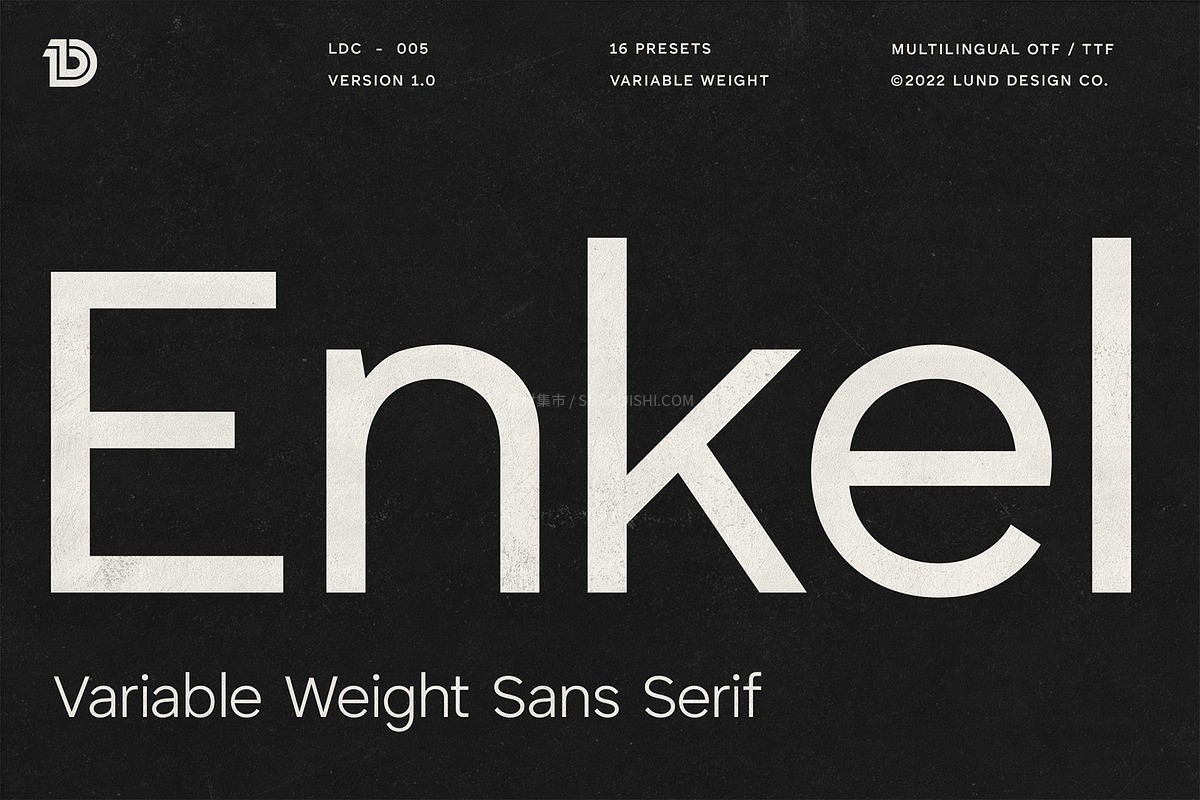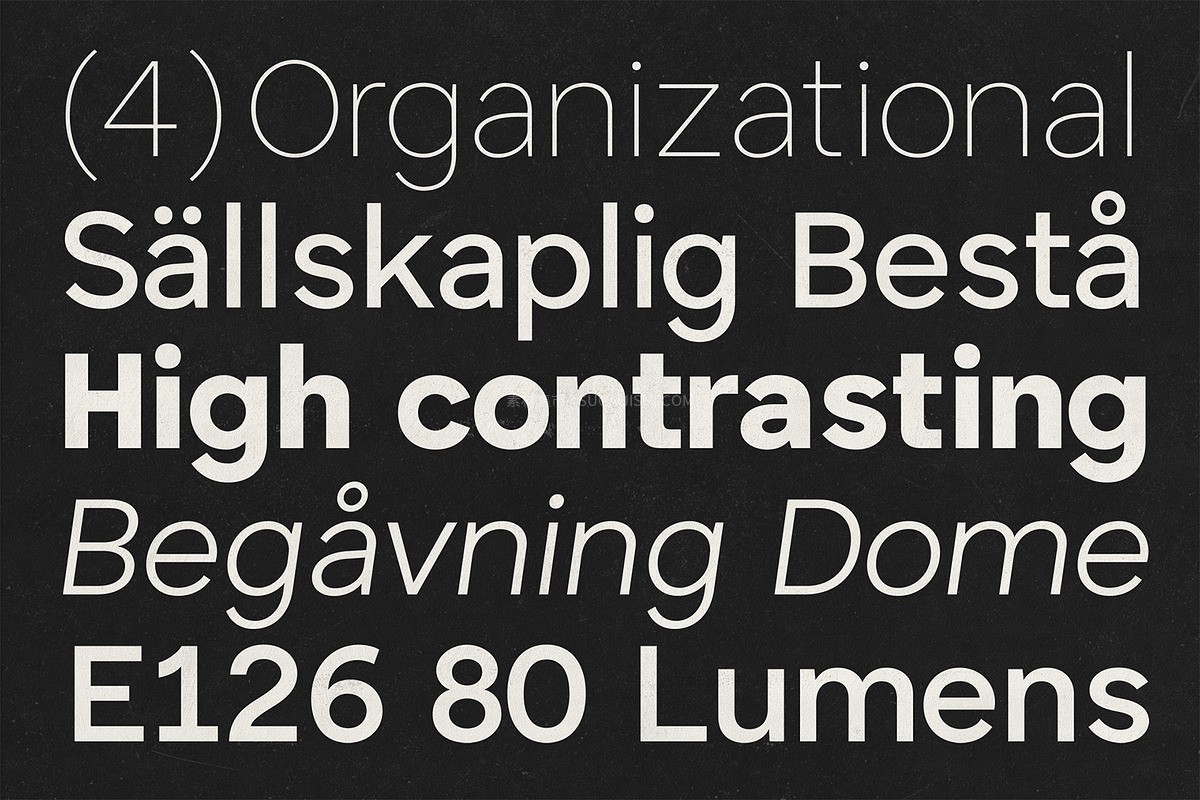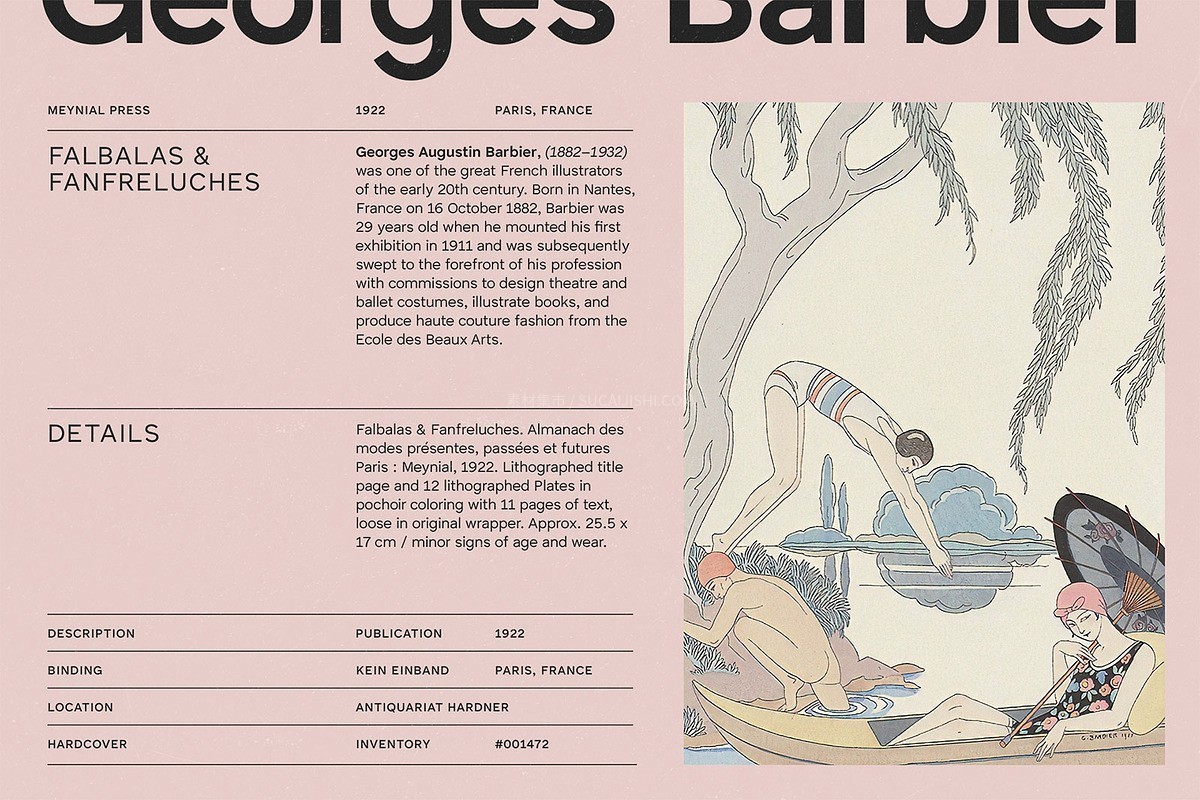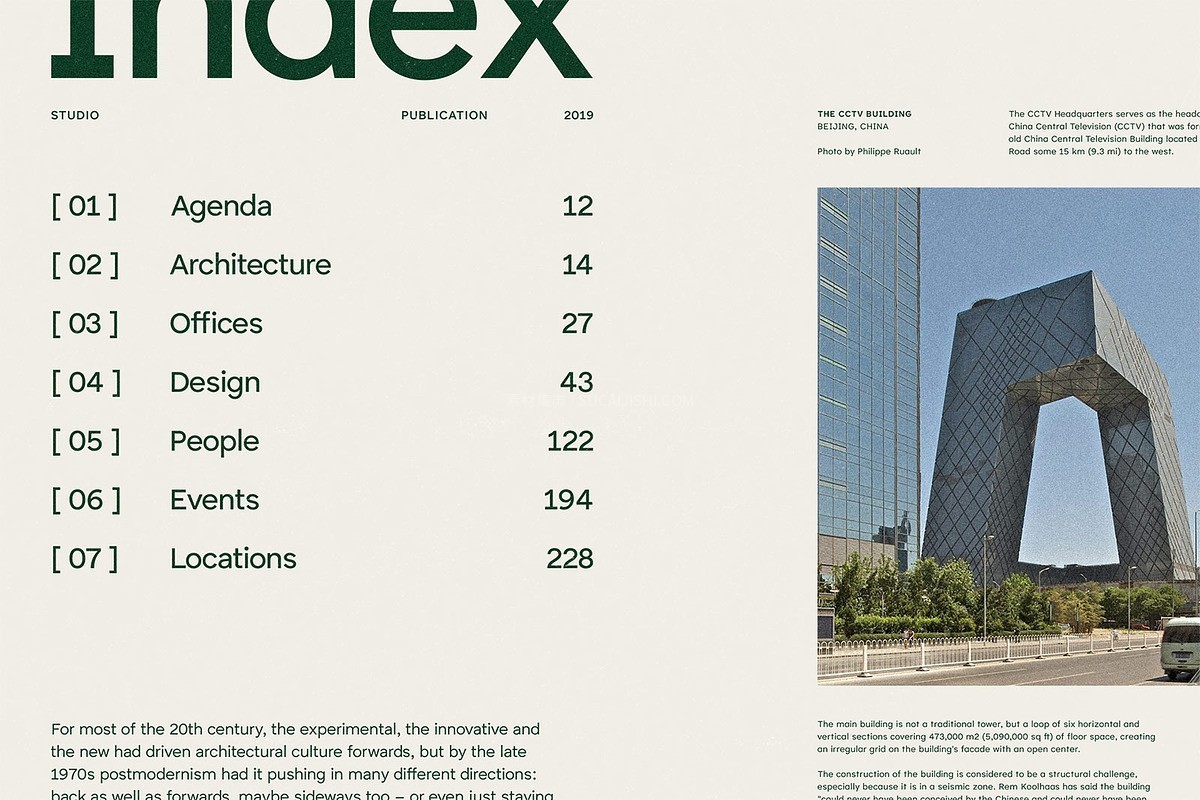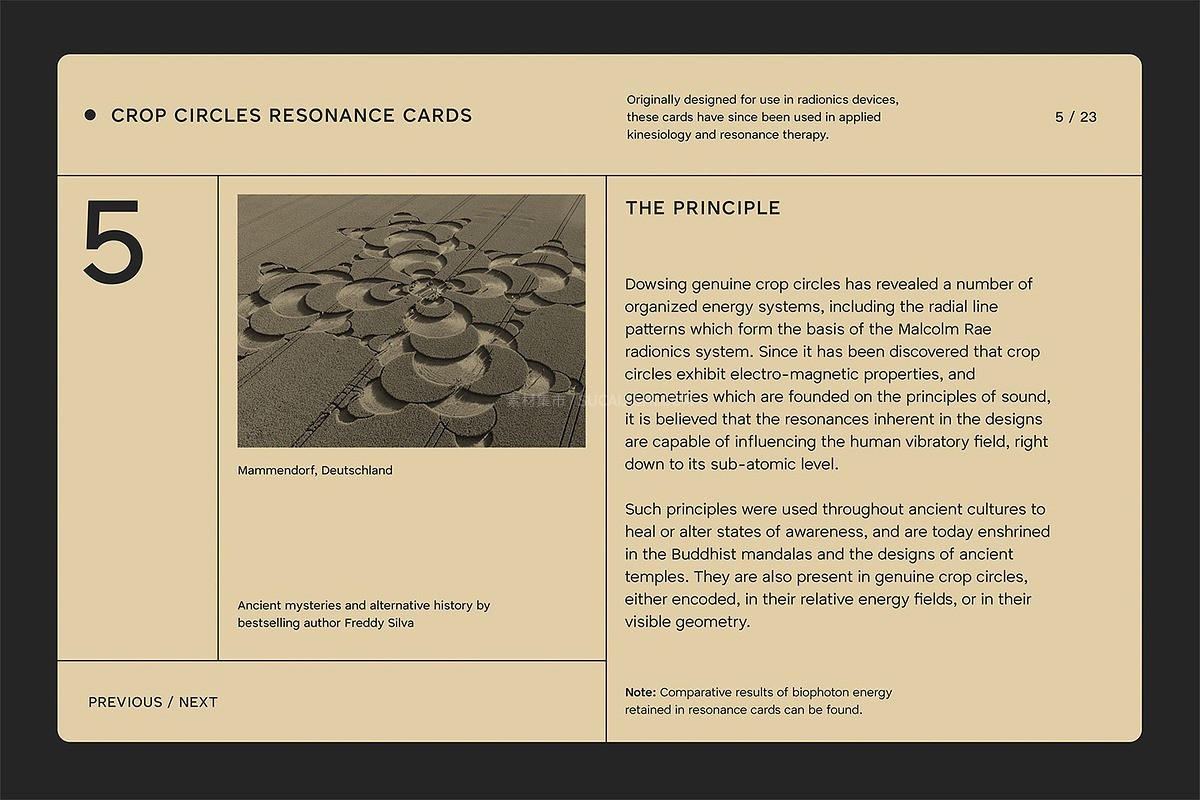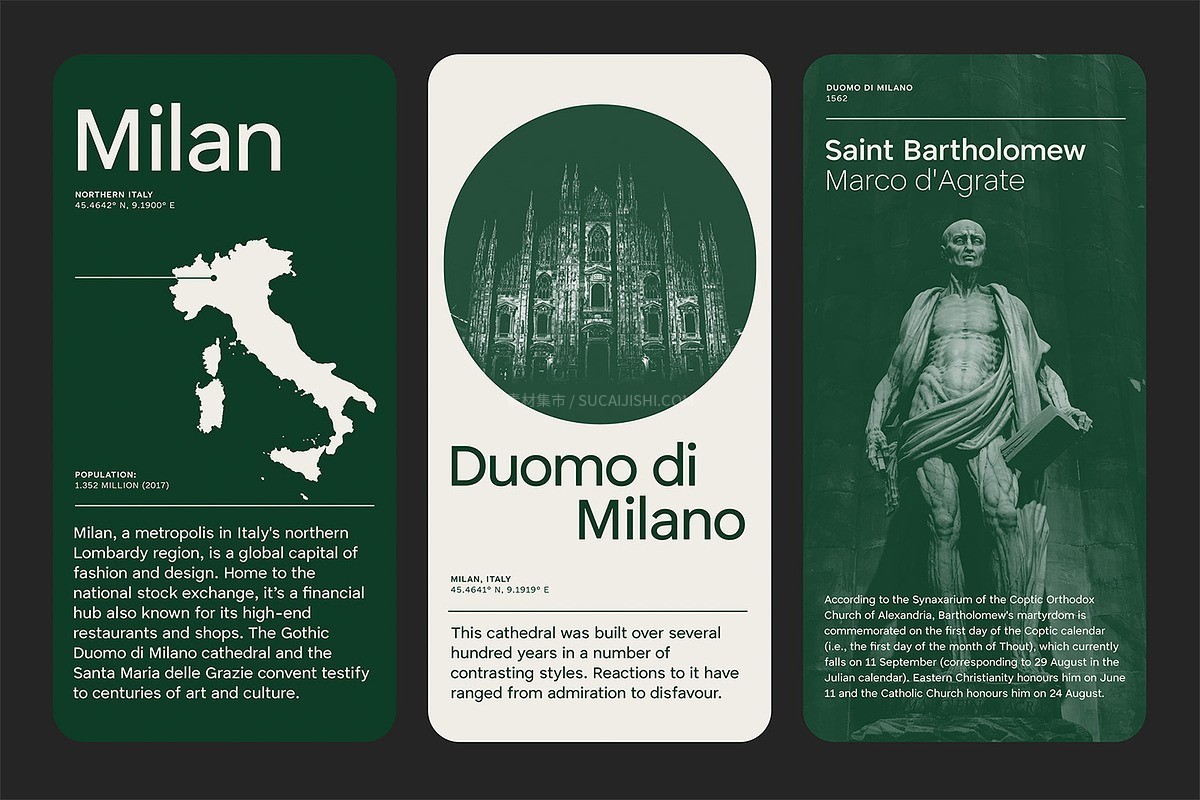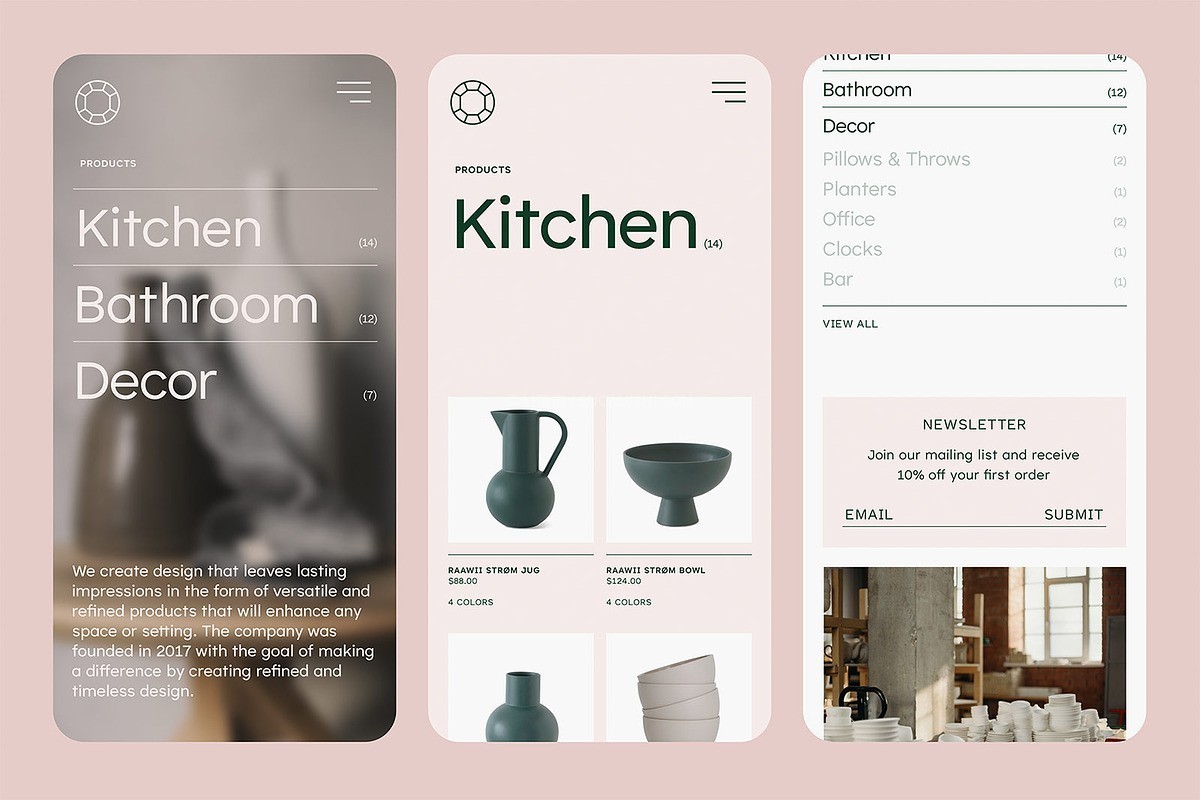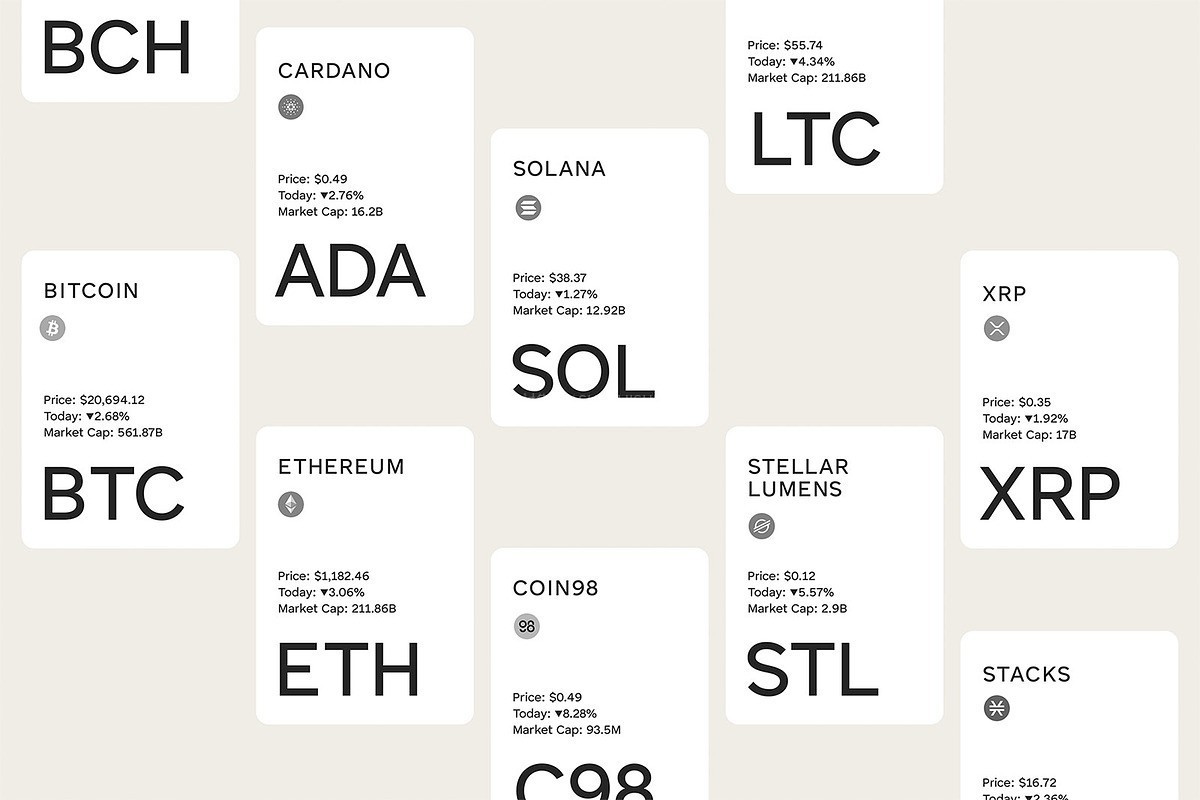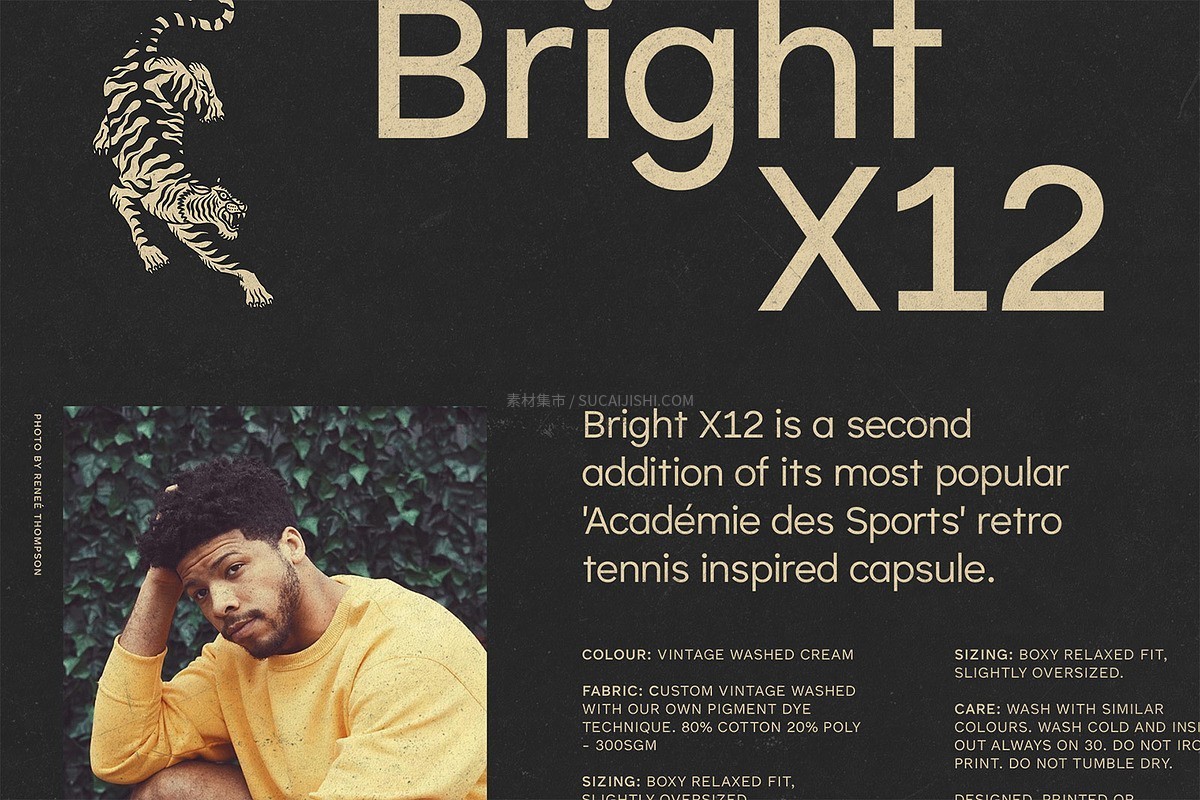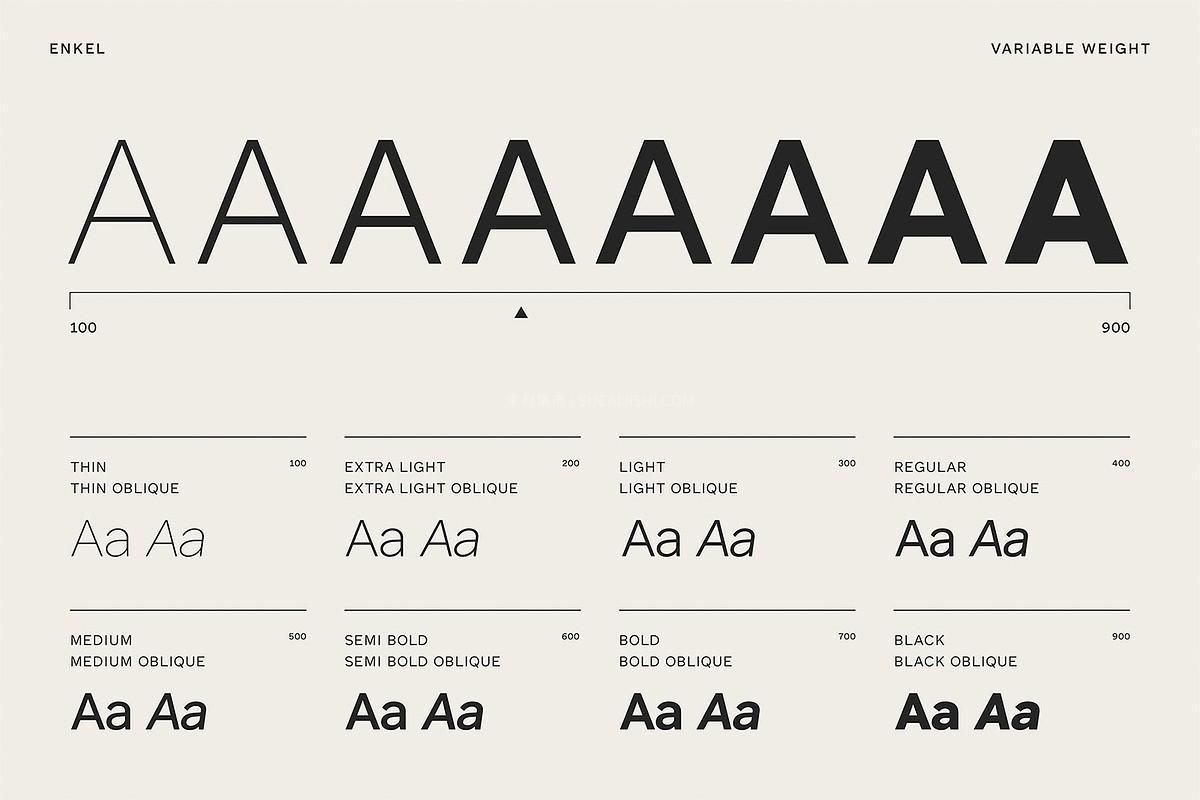
Enkel 全能无衬线可变字体包
一款超级实用的“全能型”无衬线字体家族——Enkel!它巧妙地把几何感和新无衬线风格融合在了一起,简直是排版界的万金油~用来做大字号的醒目标题时,气场全开,视觉冲击力极强;而缩放到小字号排版长文本时,又能保持极其干净清晰的易读性,一点都不累眼!它不仅支持多种样式和可变字重,连重音符号和多语言字符都给你准备得妥妥的。